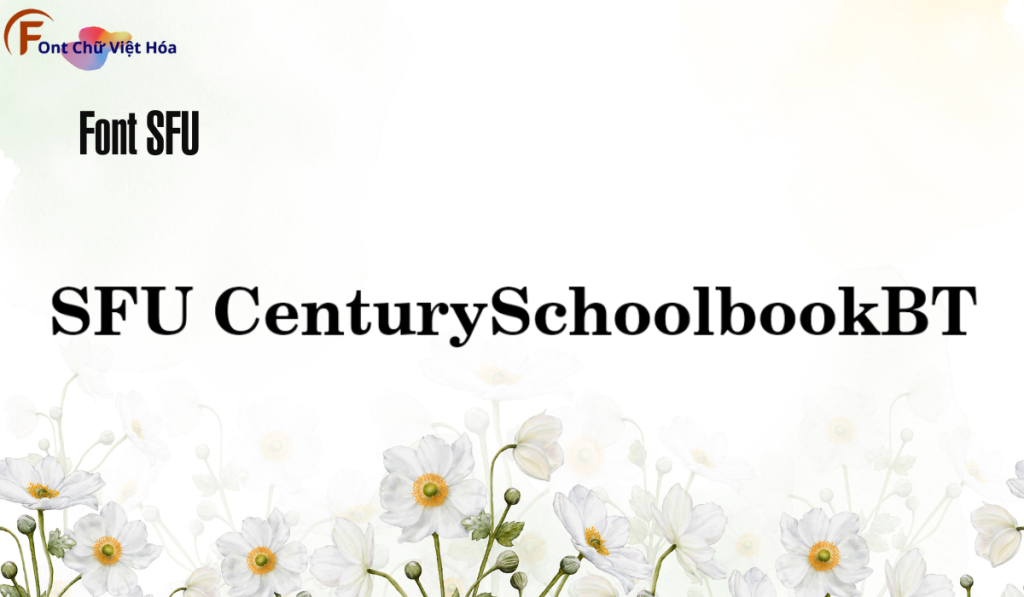
Bộ Font: SFU
Phân loại: Cổ điển
Độ dày: Regular, Bold, Italic, Bold Italic
SFU Century Schoolbook Bt Việt Hóa, thuộc bộ font SFU, mang phong cách serif cổ điển với các đường nét thanh thoát và tinh tế. Font này được thiết kế nhằm mục tiêu tạo ra sự sang trọng và dễ đọc, đặc biệt phù hợp cho các thiết kế như sách, báo, và tài liệu. Đặc điểm hình dạng của SFU Century Schoolbook Bt là các đường nét rõ ràng và tỷ lệ chữ cân đối, giúp tạo ấn tượng thị giác mạnh mẽ và tối ưu hóa không gian trong thiết kế. Font này cũng đã được Việt hóa, mang đến sự linh hoạt và tiện dụng cho các dự án thiết kế bằng tiếng Việt, giúp người dùng dễ dàng tiếp cận và sử dụng.